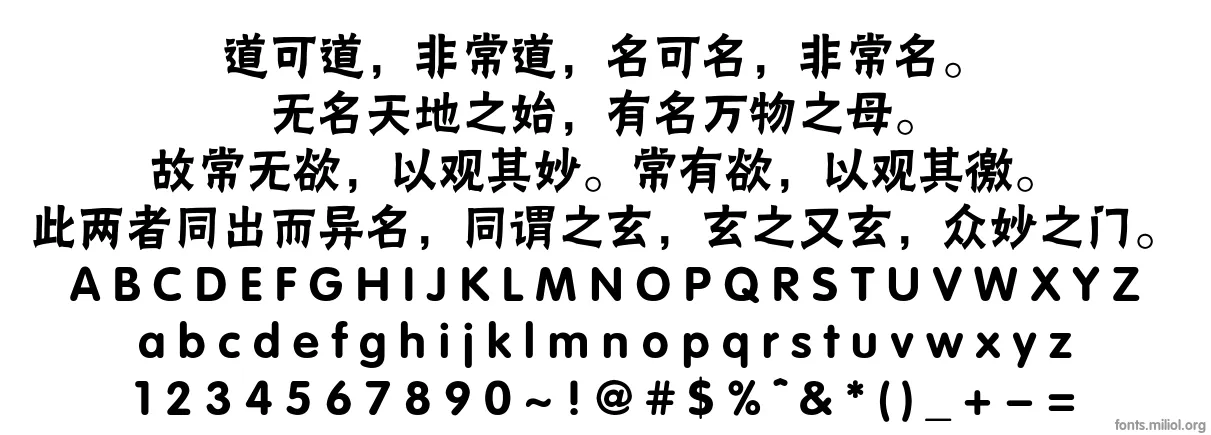
方正艺黑简体 (FZYiHei-M20S) (FZYHJW--GB1-0) 字体下载
**方正艺黑简体:现代设计中的优雅之选**
方正艺黑简体(FZYiHei-M20S)是一款兼具艺术感与实用性的中文字体,其设计融合了黑体的稳重与手写笔触的灵动,适用于标题、广告、品牌标识等视觉场景。字体线条干净利落,笔画末端略带弧度,既保留了黑体的易读性,又增添了独特的个性风格。FZYHJW--GB1-0编码版本兼容GB2312标准,支持简体中文显示,能够满足印刷、数字媒体等多场景需求。
这款字体尤其适合追求现代感与人文气息的设计项目,如文化宣传、时尚杂志或产品包装。其优雅的形态在放大时细节分明,小字号下仍保持清晰度,展现了方正字库对汉字美学的深刻理解。无论是商业设计还是艺术创作,方正艺黑简体都能为作品增添一抹精致的视觉语言。